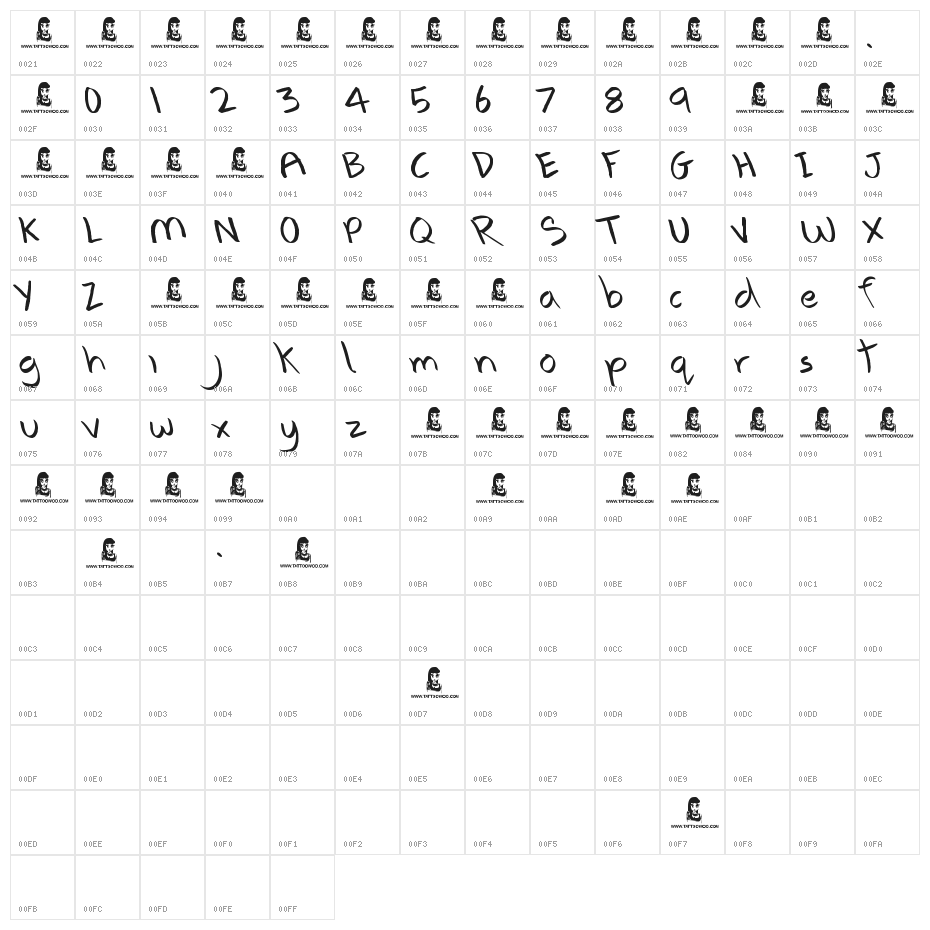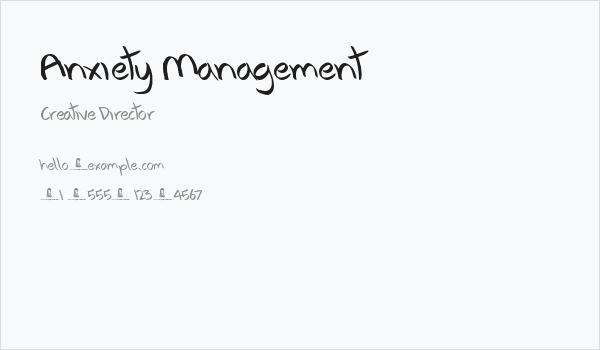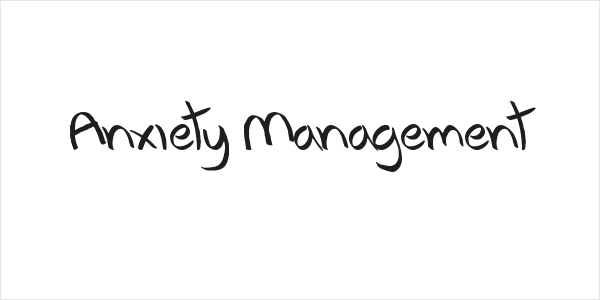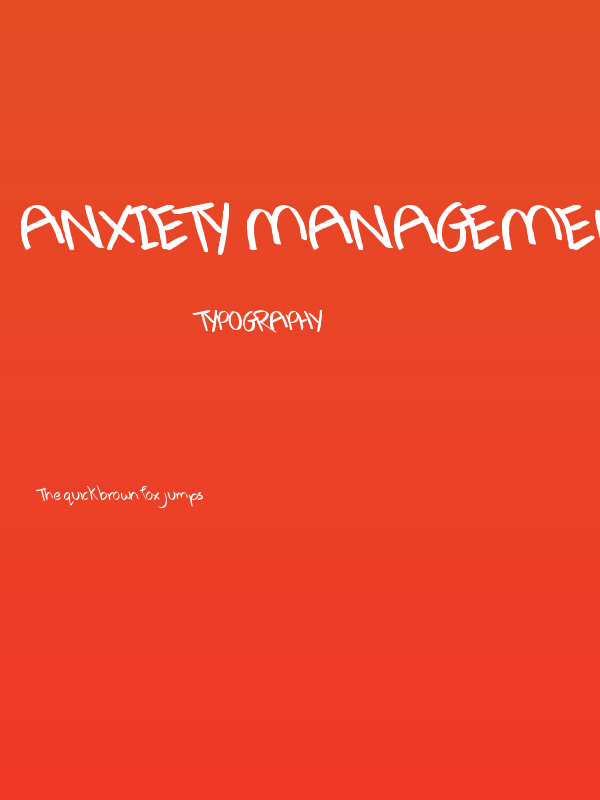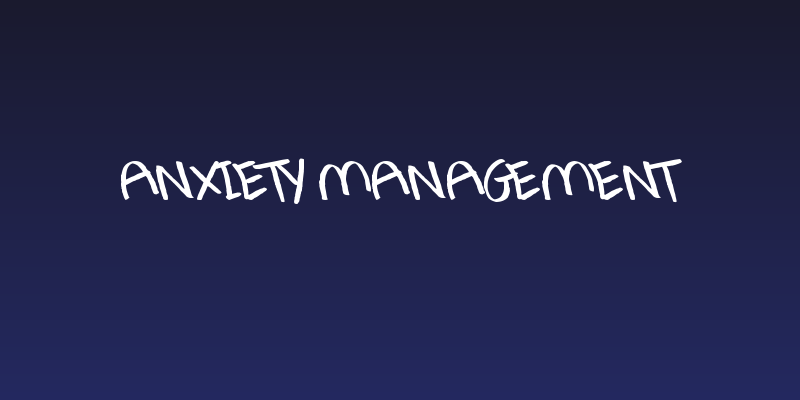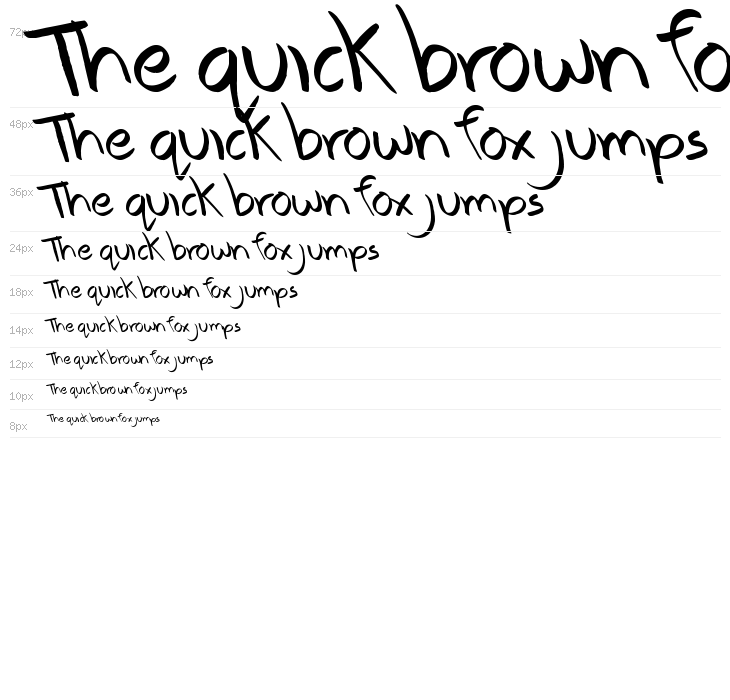
Anxiety Management Font
| Stile generale | Playful, Energetic |
| Caso d'uso | Headlines, Logos, Creative projects |
| Progetti proposti | Ideal for creative projects such as greeting cards, posters, children's books, and branding materials that require a personal touch. |